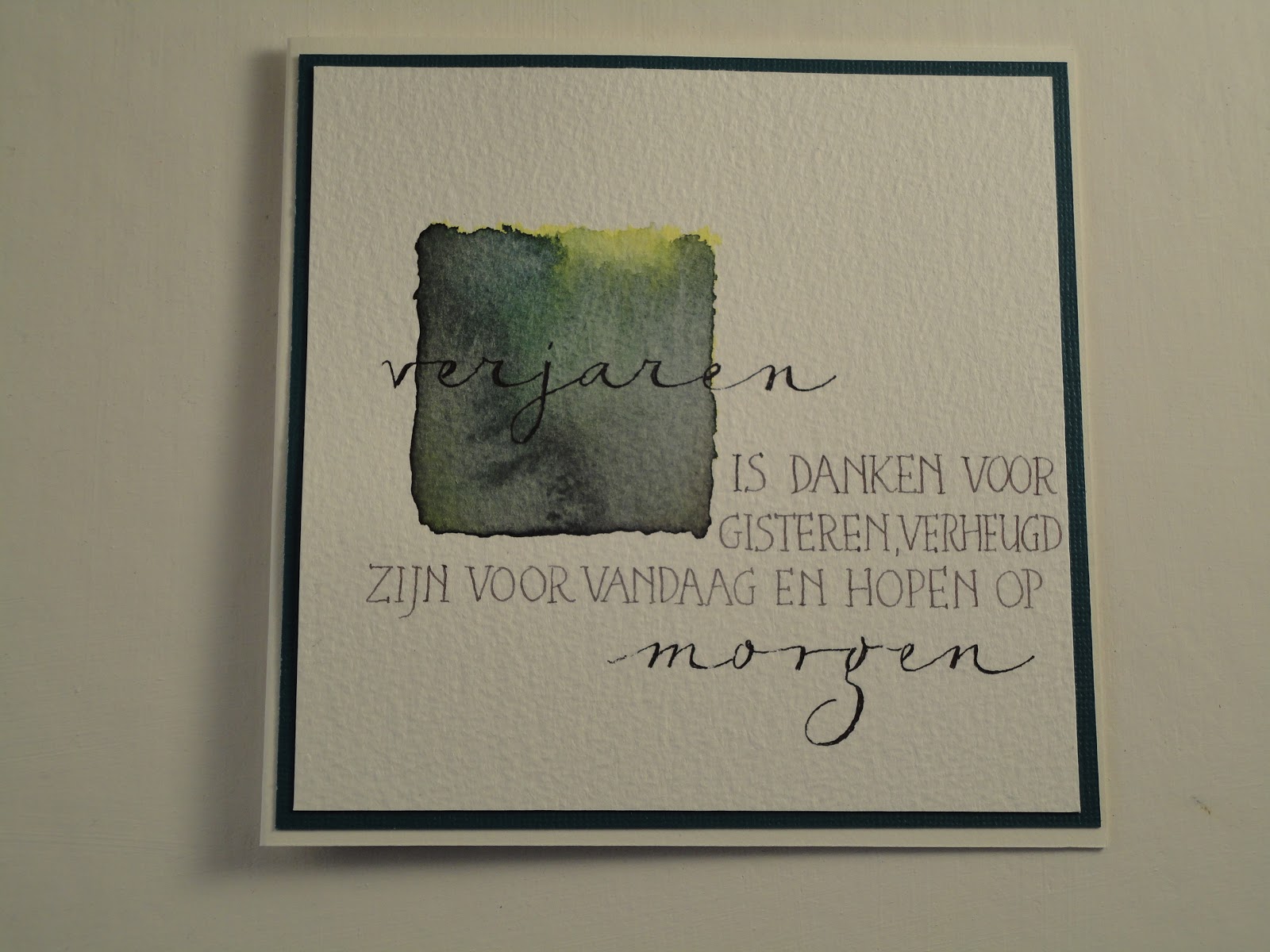
today is special
De zwarte tekst is gehandletterd met de zwarte tombow fude brush pen (soft tip).
Voor 'bijzonder' gebruikte ik de witte gel pen van pilot.
'There is something about every day, but today is truly special'.
I handlettered the black part of this text with the tombow fude brush pen (soft tip).
The word 'special' was done with the Pilot gel pen.
Chillida project: M and S
In maart begon ik met het Chillida-projekt als uitdaging voor mezelf. De L, K, R en F passeerden al de revue. (klik rechts onder 'labels' op het woord Chillida om ze nog eens te zien)
Vandaag is het de beurt aan de M en de S.
In March I started the Chillida project as a challenge to myself.
This month I created the letters M and S.
Van de M maakte ik nog een speciale versie voor een verjaardagskaart.
I made a special version of the M for a birthday card. :
one stamp -different cards: part 1
Met een en dezelfde stempel kan je best veel variaties bedenken.
Ik gebruikte hier een bloemenstempel van 'stampotique' en bestempelde deze met versamark inkt.
Wat wit wow-embossingpoeder erover en laten smelten. Dan knipte ik het bestempelde papier wat kleiner, omdat ik niet de hele stempel dacht nodig te hebben.
De bloemblaadjes kleurde ik (snel en slordig), maar bewust) in met aquarelverf .
With one and the same stamp it is possible to come up with quite a few variations.
Here I used a flowerstamp by 'Stampotique' and embossed it in white. I cut out the stamped paper a little smaller 'cause I didn't need the whole stamped image here.
Ook probeerde ik voor elke kaart een ander (schrijf)materiaal te gebruiken. En zo kwam ik tot de volgende resultaten :
And for every single card I also used a different writing material. That's how these cards were realised:
| tekst in speelse kapitalen in potlood- capitals in pencil+relief paint for the middle of the flower |
| white gel pen for the text 'happy birthday' |
| text written with a pointed pen in bleedproof white ink |
a big kiss...
Father's Day
Het begon al met de kleur ....
Maar soms mag je je laten helpen door het toeval: ik had op en naast mijn werktafel nog een aantal potjes met nog een weinig gouache erin - alles samen gegoten, en zo kwam ik aan dit blauw.
De tekst dan in gewone kapitaaltjes met een 'fantasietje', gecombineerd met het woord 'gefeliciteerd' in uitgerokken schrift.
En als je dan eenmaal toch de compositie hebt, kan je er evengoed nog een paar maken, dacht ik:
Men are not the easiest "cases" to make cards for and that also goes for my own father. The colour for one.So I let chance help me with this card; I had some small amounts of leftover gouache on my desk, poured them together in a small jar and that's how I got this blue.
I then wrote the text in these 'phantasy' capitals and the word 'gefeliciteerd/proficiat' (meaning: congratulations) in a stretched italic kind of way. Once I had the composition I liked, I decided to make two more :
| links in bister en rechts met rode tekeninkt |